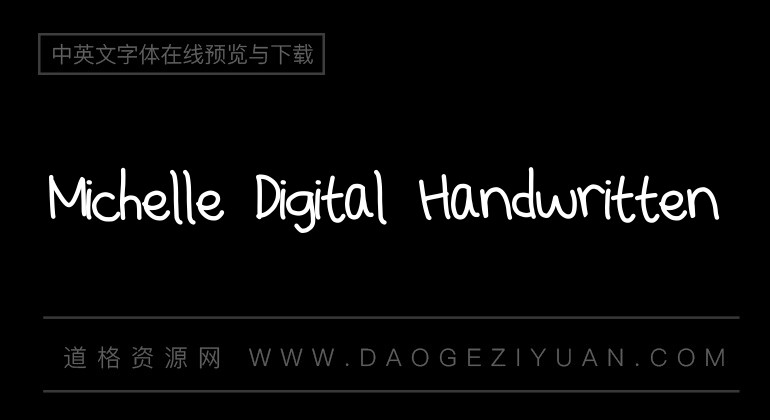
Michelle Digital Handwritten 字体是一款手写体字体,由微软的设计师 Michelle J. Li 创作,可以用于创建现代、温暖的设计风格。它的特点是清晰的字形,每个字母都有细腻的线条,让字体看起来更加活泼,有着自然的手写外观。它具有良好的可读性和可视性,适用于各种场景,如品牌标志、海报、卡片、招贴、礼品、书籍封面等。内容介绍
Michelle Digital Handwritten是一款非常不错的手写艺术字体,具有很好的视觉感,适合于文化类的宣传设计、商业类品牌的广告和产品包装设计以及个性化文字排版等较多场景。